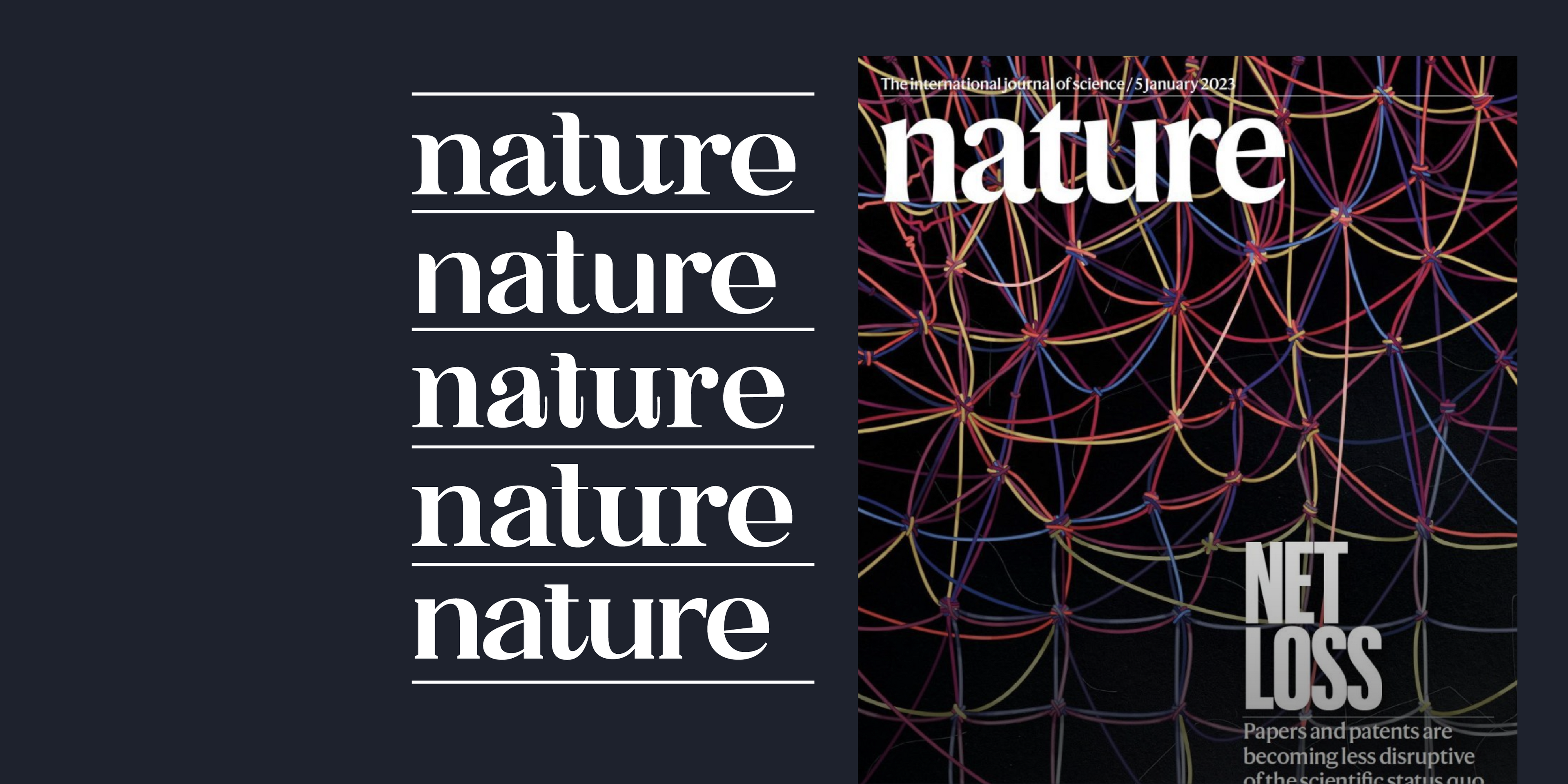
“Harding”, la fuente personalizada de la naturaleza
En octubre de 2019, la revista Nature Journal presentó una actualización de su logotipo, que incluía una nueva tipografía personalizada, “Harding”, que lleva el nombre de la fallecida neuróloga Anita Harding. En su artículo “Las decisiones de diseño detrás del nuevo aspecto de Nature”, la directora creativa Kelly Krause muestra la evolución del diseño del logotipo de Nature a lo largo de los últimos 150 años y expone las consideraciones técnicas y estratégicas de la marca que se tuvieron en cuenta para el rediseño.
Junto con diseñadores externos, el equipo se propuso garantizar que el nuevo tipo de letra pudiera hacer frente a diversas necesidades de material científico, considerando ecuaciones, letras griegas y caracteres especiales comúnmente utilizados en artículos académicos, además de incorporar una amplia gama de caracteres adicionales como símbolos astronómicos y fonemas encontrados en idiomas africanos.
Actualización del logotipo de Nature Journal. Izquierda: logotipo antes del rediseño de 2019. Imágenes: capturas de pantalla de Twitter.
Fuentes similares en tono a “Harding”
Al diseñar “Harding”, Krause destaca que el tono general buscado era una sensación de calma e inteligencia racional, combinada con un toque de formalidad e ingenio británicos.
Si buscas fuentes con un tono similar, consulta estos cinco tipos de letra:
1. Bauhaus Suave
Bauhaus Soft se presenta en nueve grosores de fuente, desde Thin hasta Black. El grosor más cercano al logotipo de Nature es Medium (500). El enfoque de la tipografía en cuanto al tono es "orgánico" debido a su naturaleza redondeada, por ejemplo, una bola terminal pronunciada en la letra r y una cola redondeada en la letra a.
2. Bauhaus en
Con un estilo más accesible, Bauhaus Chez elimina las serifas (pequeños pies que sobresalen de los tallos de las letras) y tiene tallos redondeados en la parte superior derecha, los cuales se suman a una apariencia general más amigable.
3. Kijs
La tipografía Kijs es una fuente serif natural con mucho carácter. Las colas suelen ser alargadas con un trazo similar al de un bolígrafo, lo que añade un toque de sensación de escritura a mano al diseño de la tipografía. Los trazos de alto contraste y las letras más distintivas que se destacan (pero que se pueden intercambiar con alternativas de diseño mediante un programa de maquetación) hacen de la fuente Kijs una fuente de exhibición y perfecta para logotipos.
4. Mod
Similar a Bauhaus Soft, Bauhaus Mod es una tipografía serif moderna. Las serifas son ligeramente más prominentes de lo habitual, lo que le da a esta fuente presencia y fuerza. Los contrafuertes de Mod están muy abiertos y los trazos de la línea base están cortados de manera recta, lo que crea un equilibrio entre masculino y femenino.
5. Quil
Quil Medium (500) tiene serifas cortas y terminales de corte recto, dos características de diseño que crean una sensación objetiva y más distante. La franqueza se equilibra con colas largas, por ejemplo, en la letra t.